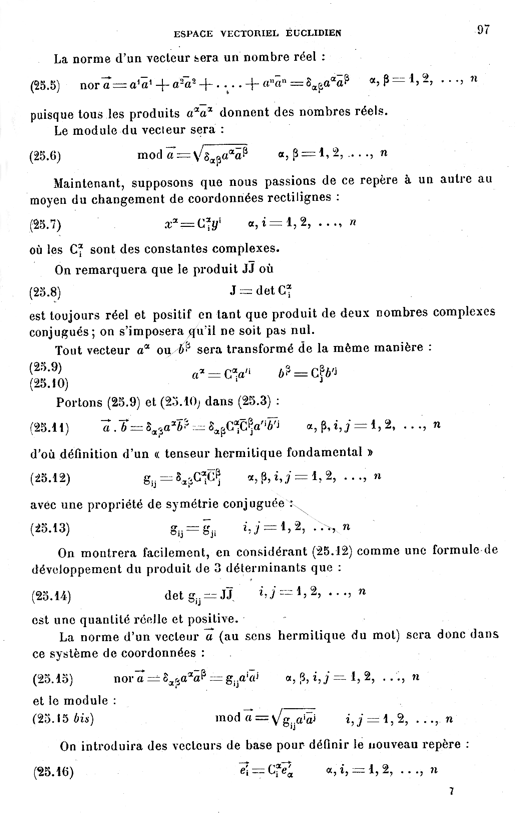
Thierry Bouche a écrit :
Le jeudi 8 mars 2007, vers 11:28:24, Jean-Luc BLARY écrivit : JL> Si vous incorporez - sur une ligne bien séparée, ce qui est le cas de la JL> demande - un texte en arabe, allez-vous l'écrire de gauche à droite sousJL> prétexte qu'il fait partie du discours, ou allez-vous respecter ses JL> règles spécifiques ?Si les formules mathématiques étaient un système d'écriture en soi, pourquoi les traditions typographiques changeraient-elles en fonction de la langue dans lesquelles elles se trouvent ? (votre exemple n'est pas mauvais, puisque la tradition typographique arabe écrit les maths de droite à gauche, avec des signes de somme ou d'intégrale inversés, par exemple !) Mais grâce à votre remarque, je viens de comprendre la ligne de partage entre les deux écoles : quand les maths sont un élément familier du discours (textes de recherche ou destinés à des scientifiques confirmés), on ponctue ; quand c'est du chinois (pour le typo, les protes, les lecteurs...?), on laisse comme c'est !
Non, ce serait plutôt le contraire.Ci-joint une page scannée, prise au hasard dans le premier bouquin de math qui m'est tombé sous la main (un cours de calcul tensoriel).